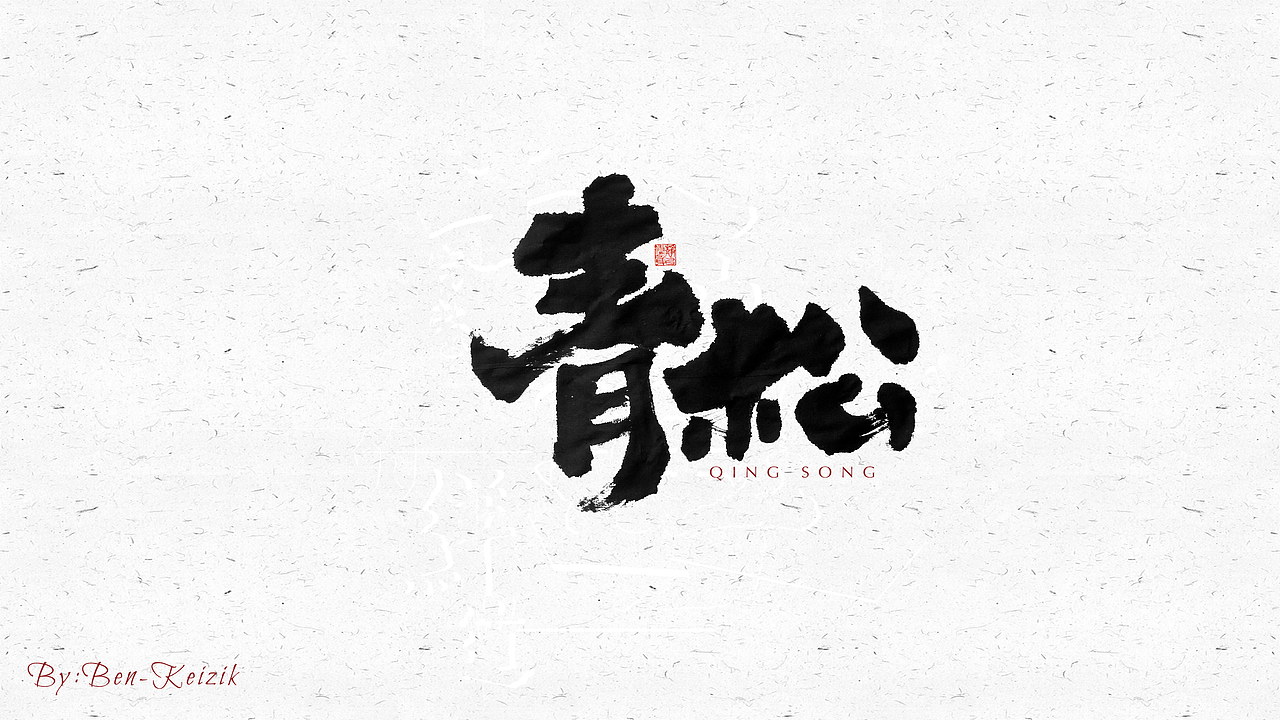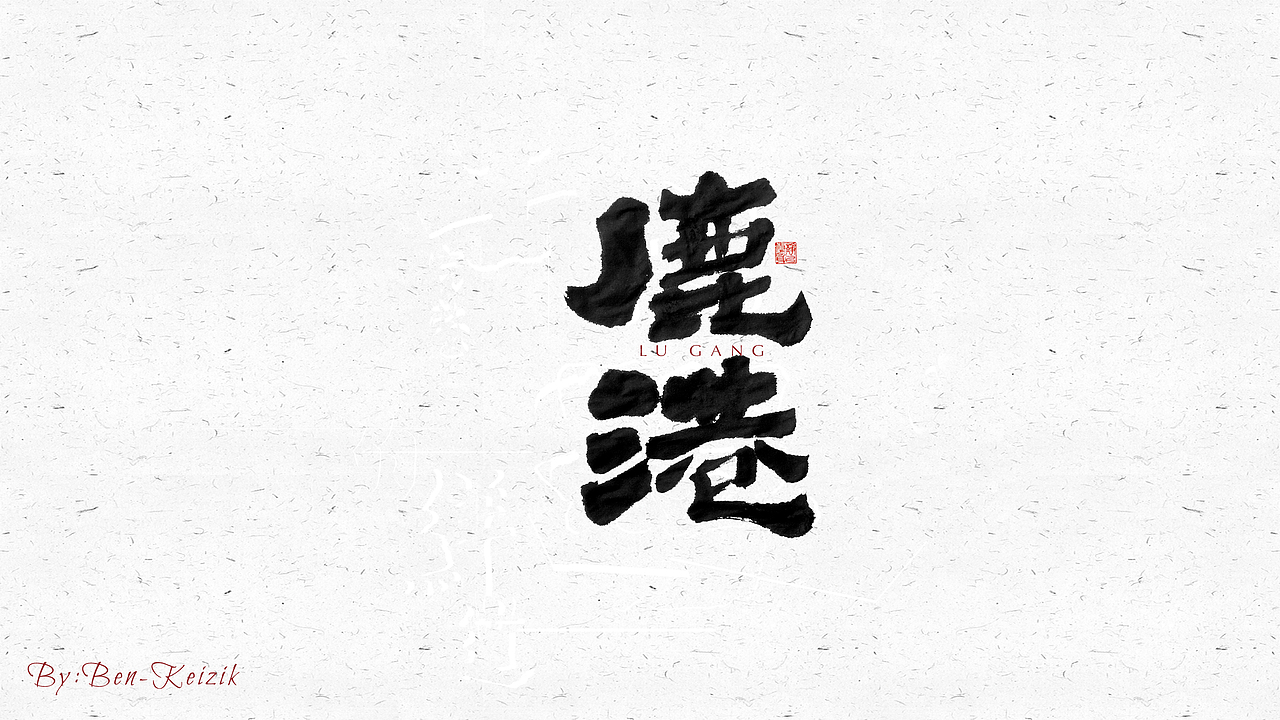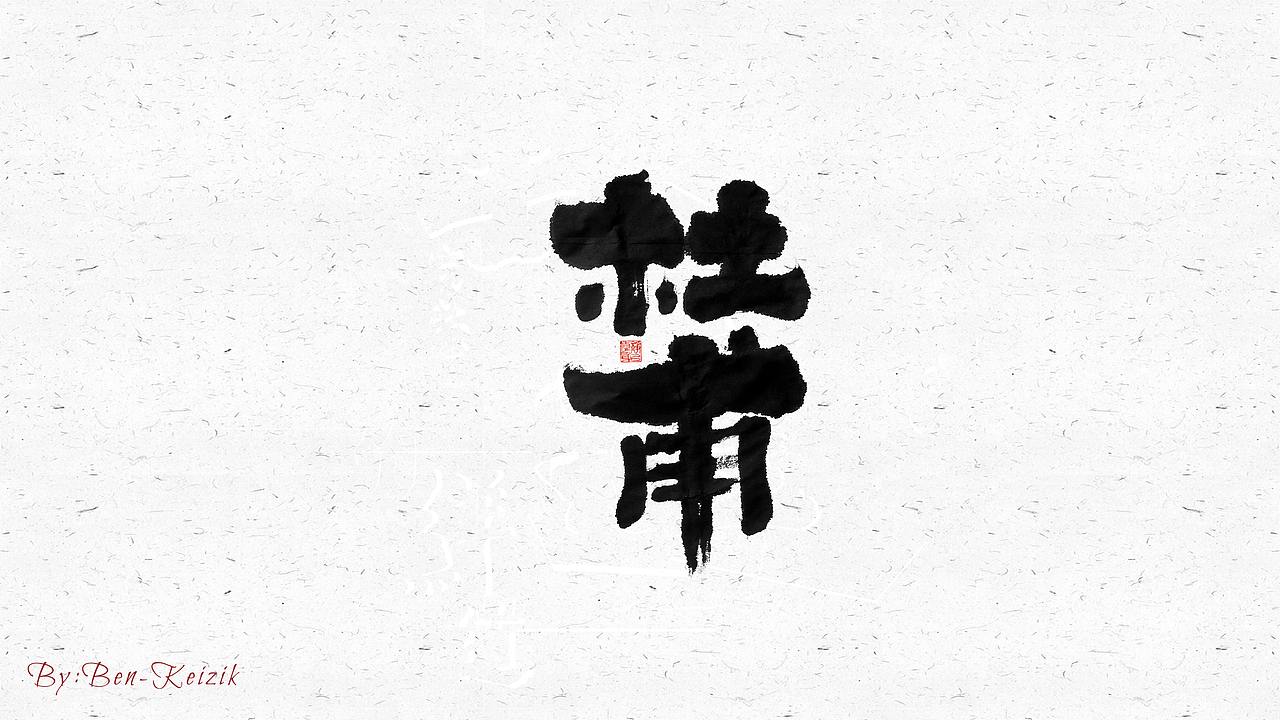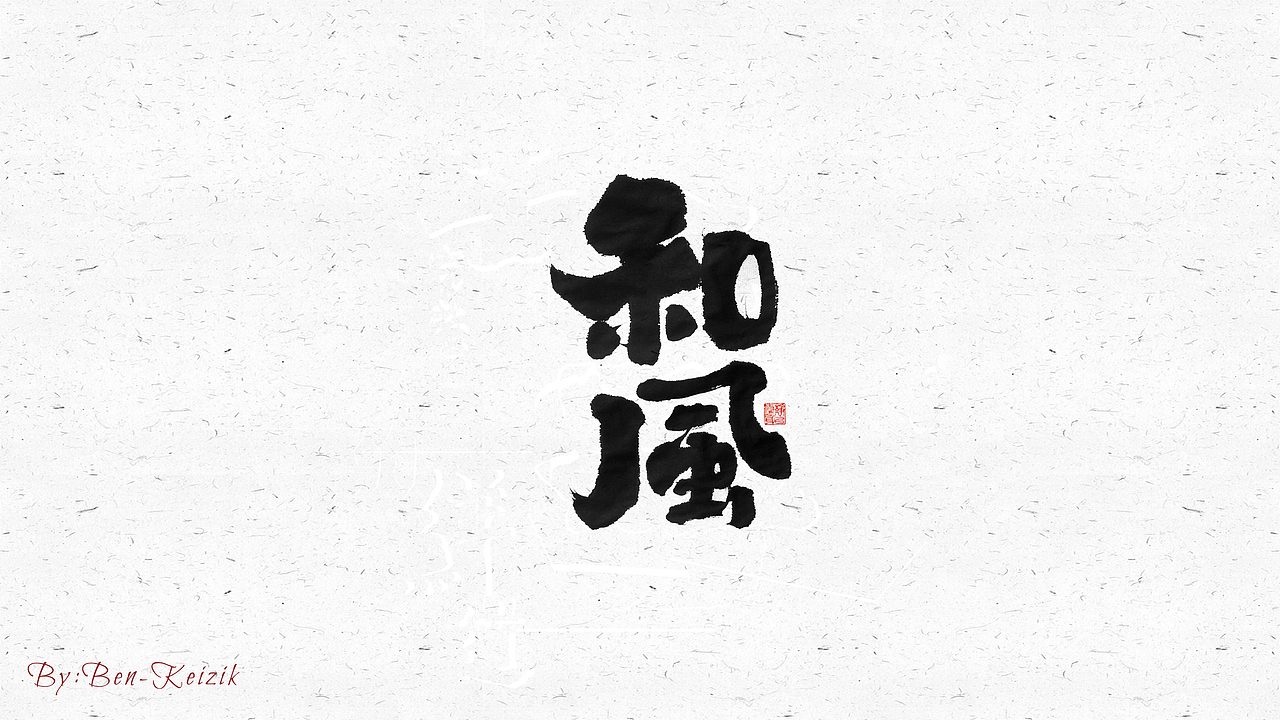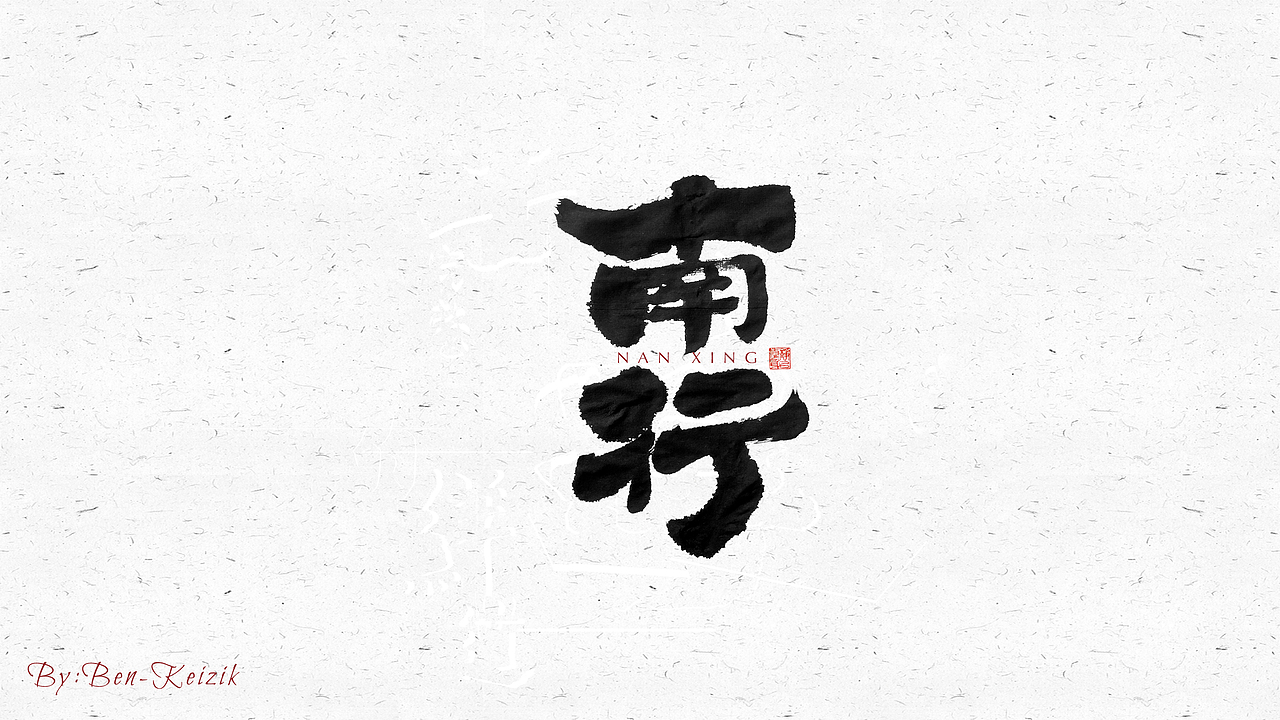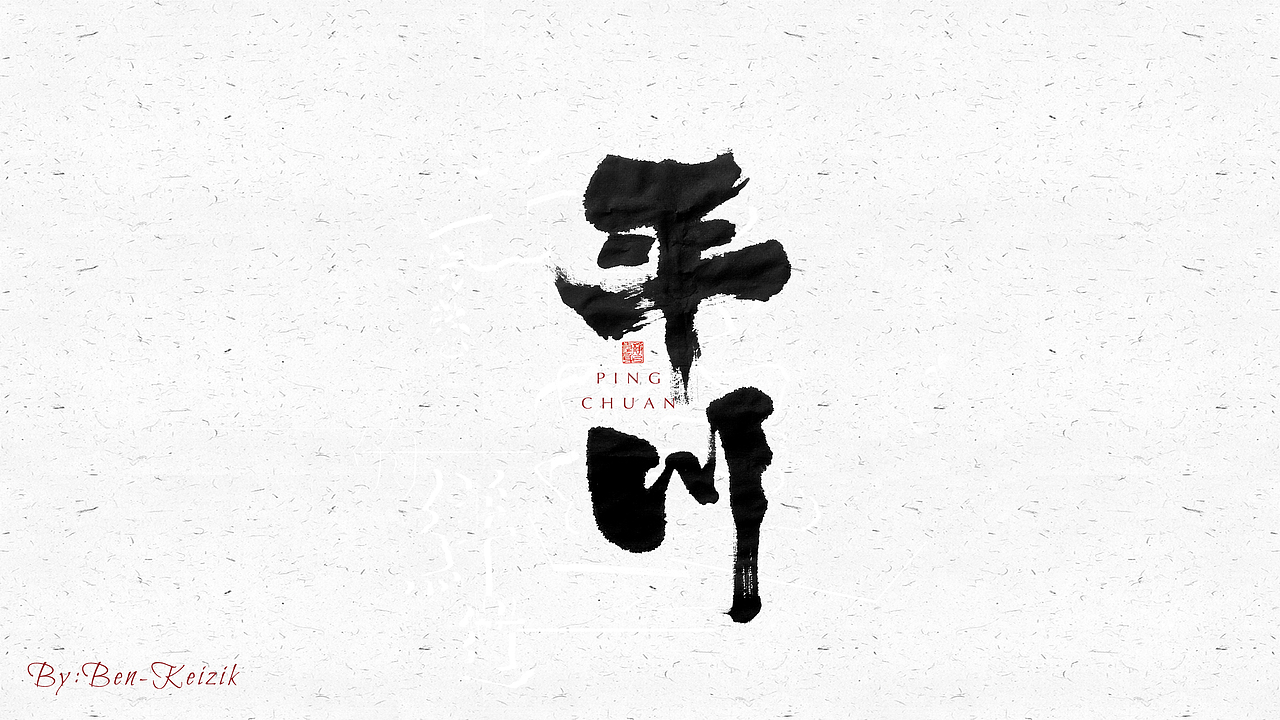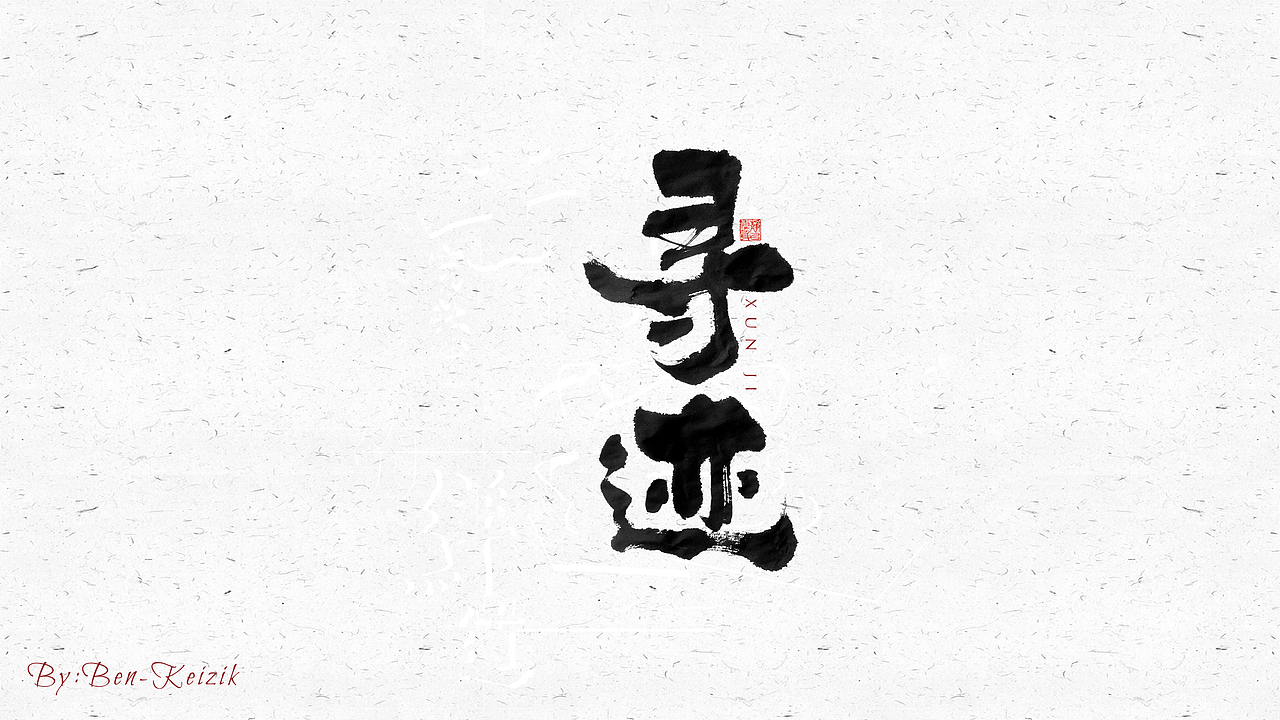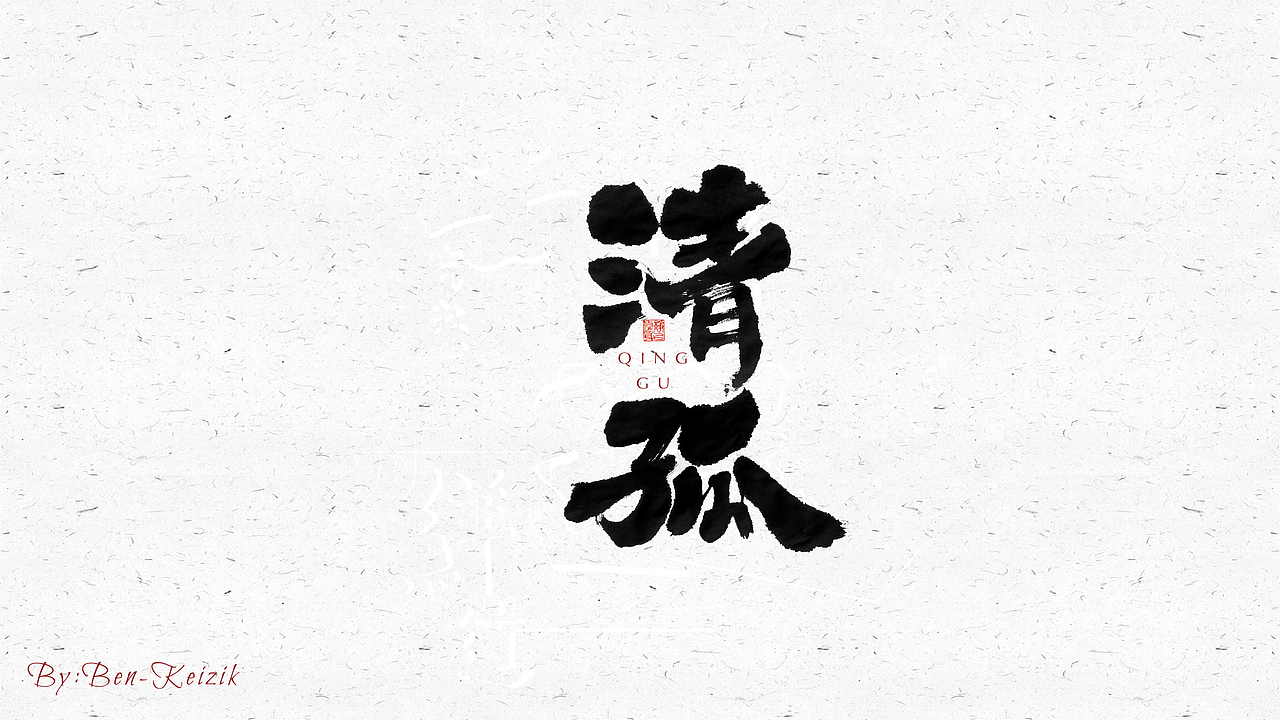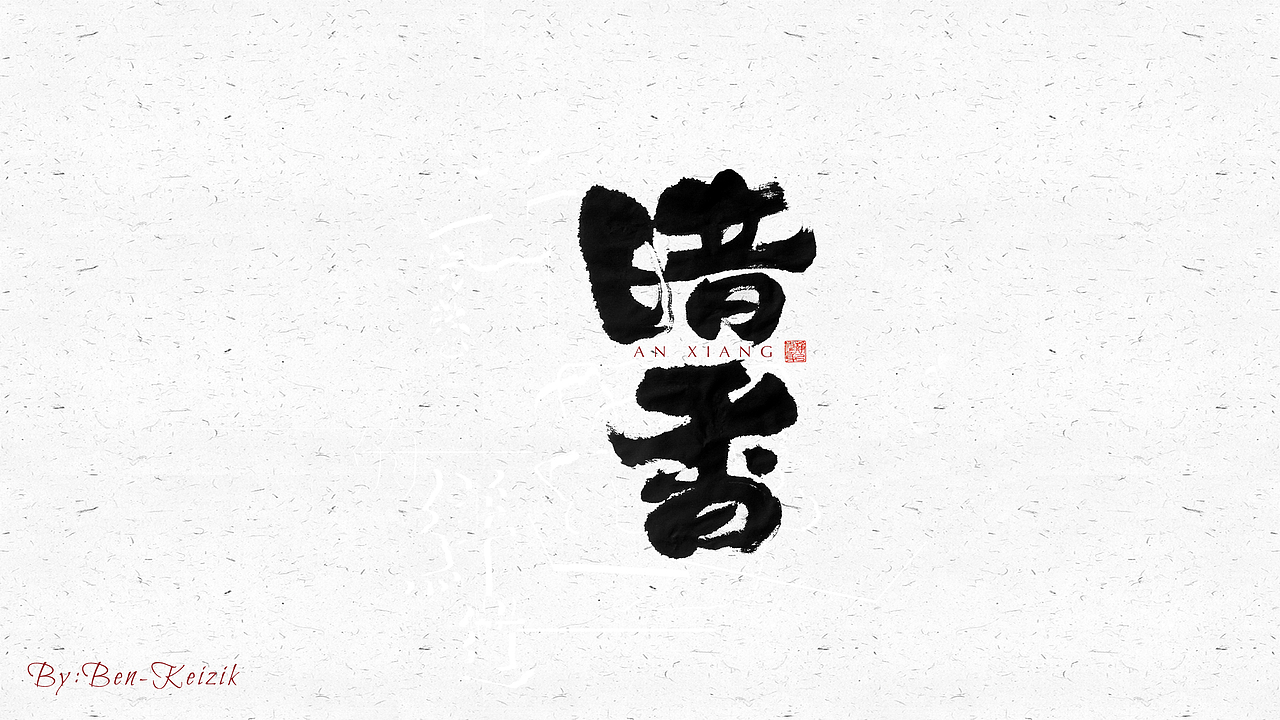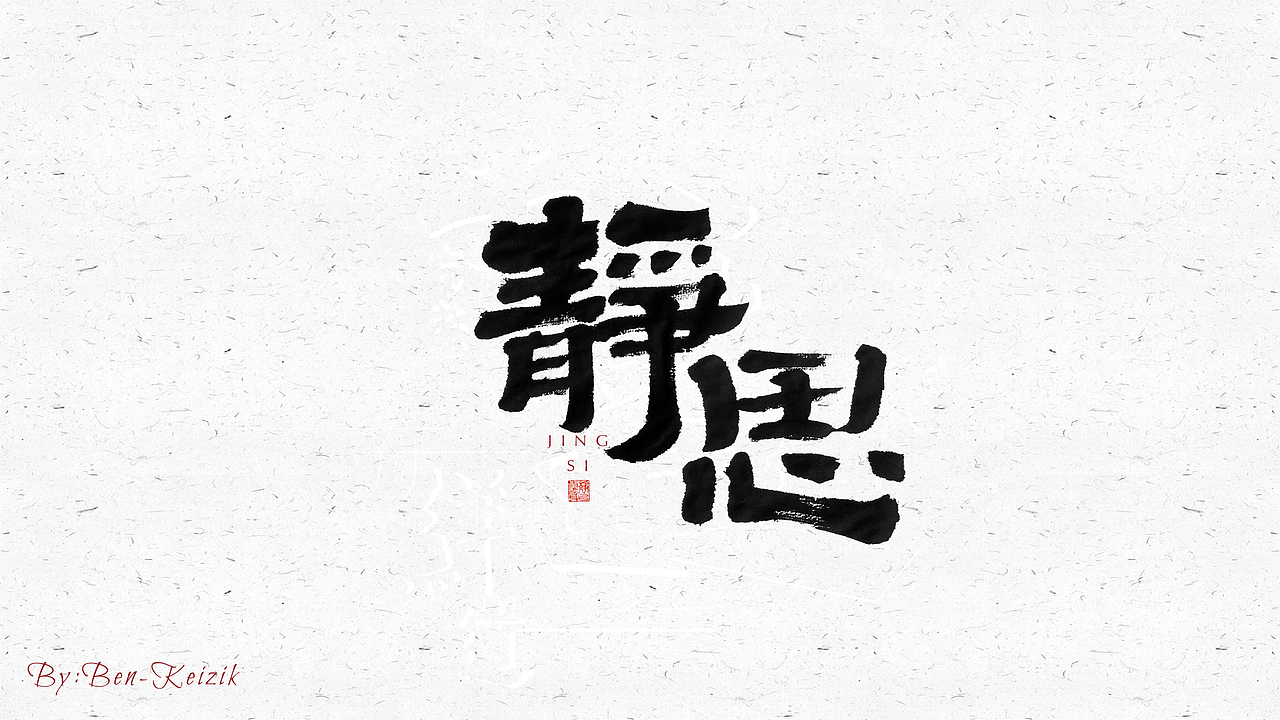
自言字语 —— 一组手写毛笔字(图ZMjQyMzMyMDUy) - 字体/字形 - 站酷设计师祺壹原创素材 - 站酷ZCOOL
自言字语 —— 一组手写毛笔字(图ZMjQyMzMyMDQ4) - 字体/字形 - 站酷设计师祺壹原创素材 - 站酷ZCOOL
自言字语 —— 一组手写毛笔字(图ZMjQyMzMyMTA0) - 字体/字形 - 站酷设计师祺壹原创素材 - 站酷ZCOOL
自言字语 —— 一组手写毛笔字(图ZMjQyMzMyMDM2) - 字体/字形 - 站酷设计师祺壹原创素材 - 站酷ZCOOL
自言字语 —— 一组手写毛笔字(图ZMjQyMzMyMDEy) - 字体/字形 - 站酷设计师祺壹原创素材 - 站酷ZCOOL
自言字语 —— 一组手写毛笔字(图ZMjQyMzMyMDE2) - 字体/字形 - 站酷设计师祺壹原创素材 - 站酷ZCOOL
自言字语 —— 一组手写毛笔字(图ZMjQyMzMyMDMy) - 字体/字形 - 站酷设计师祺壹原创素材 - 站酷ZCOOL
自言字语 —— 一组手写毛笔字(图ZMjQyMzMyMDAw) - 字体/字形 - 站酷设计师祺壹原创素材 - 站酷ZCOOL
自言字语 —— 一组手写毛笔字(图ZMjQyMzMyMDIw) - 字体/字形 - 站酷设计师祺壹原创素材 - 站酷ZCOOL
自言字语 —— 一组手写毛笔字(图ZMjQyMzMyMDYw) - 字体/字形 - 站酷设计师祺壹原创素材 - 站酷ZCOOL
自言字语 —— 一组手写毛笔字(图ZMjQyMzMyMDg4) - 字体/字形 - 站酷设计师祺壹原创素材 - 站酷ZCOOL
自言字语 —— 一组手写毛笔字(图ZMjQyMzMyMDU2) - 字体/字形 - 站酷设计师祺壹原创素材 - 站酷ZCOOL
自言字语 —— 一组手写毛笔字(图ZMjQyMzMyMDA4) - 字体/字形 - 站酷设计师祺壹原创素材 - 站酷ZCOOL
自言字语 —— 一组手写毛笔字(图ZMjQyMzMyMDk2) - 字体/字形 - 站酷设计师祺壹原创素材 - 站酷ZCOOL
自言字语 —— 一组手写毛笔字(图ZMjQyMzMyMDA0) - 字体/字形 - 站酷设计师祺壹原创素材 - 站酷ZCOOL
自言字语 —— 一组手写毛笔字(图ZMjQyMzMyMDI0) - 字体/字形 - 站酷设计师祺壹原创素材 - 站酷ZCOOL
自言字语 —— 一组手写毛笔字(图ZMjQyMzMyMDQ0) - 字体/字形 - 站酷设计师祺壹原创素材 - 站酷ZCOOL
自言字语 —— 一组手写毛笔字(图ZMjQyMzMyMDgw) - 字体/字形 - 站酷设计师祺壹原创素材 - 站酷ZCOOL
自言字语 —— 一组手写毛笔字(图ZMjQyMzMyMDY0) - 字体/字形 - 站酷设计师祺壹原创素材 - 站酷ZCOOL
自言字语 —— 一组手写毛笔字(图ZMjQyMzMyMDY4) - 字体/字形 - 站酷设计师祺壹原创素材 - 站酷ZCOOL
自言字语 —— 一组手写毛笔字(图ZMjQyMzMyMDky) - 字体/字形 - 站酷设计师祺壹原创素材 - 站酷ZCOOL
自言字语 —— 一组手写毛笔字(图ZMjQyMzMyMDg0) - 字体/字形 - 站酷设计师祺壹原创素材 - 站酷ZCOOL
自言字语 —— 一组手写毛笔字(图ZMjQyMzMyMDI4) - 字体/字形 - 站酷设计师祺壹原创素材 - 站酷ZCOOL
自言字语 —— 一组手写毛笔字(图ZMjQyMzMyMDc2) - 字体/字形 - 站酷设计师祺壹原创素材 - 站酷ZCOOL
自言字语 —— 一组手写毛笔字(图ZMjQyMzMyMTAw) - 字体/字形 - 站酷设计师祺壹原创素材 - 站酷ZCOOL
自言字语 —— 一组手写毛笔字(图ZMjQyMzMyMDcy) - 字体/字形 - 站酷设计师祺壹原创素材 - 站酷ZCOOL